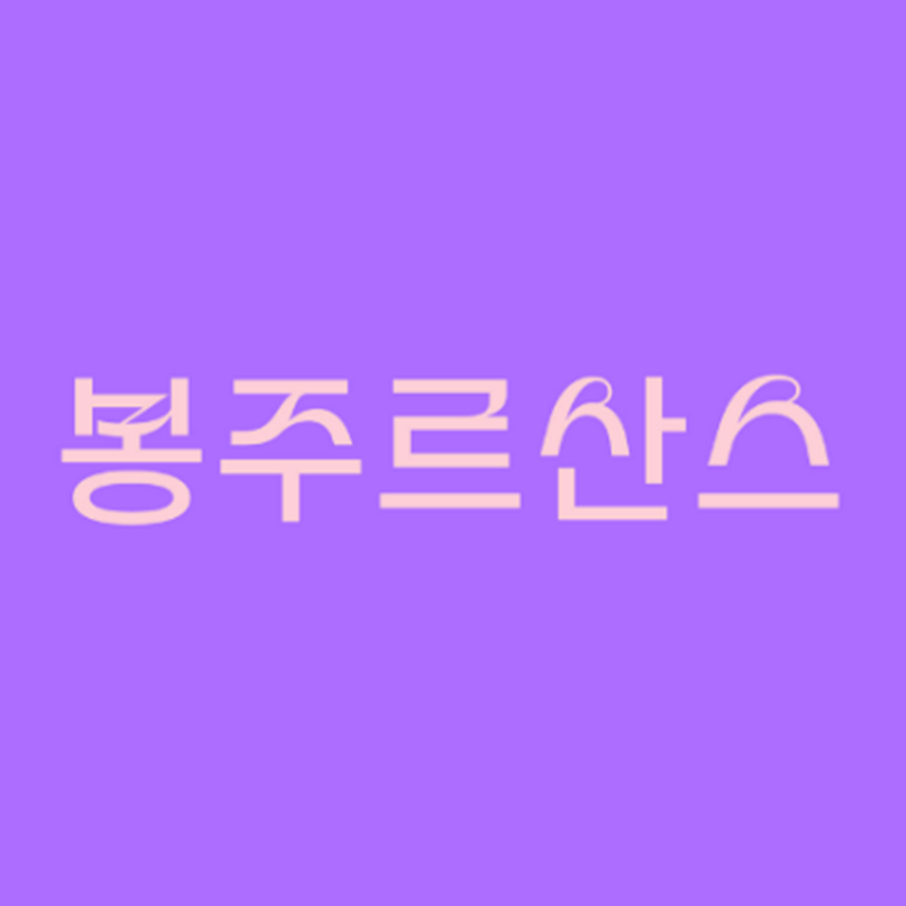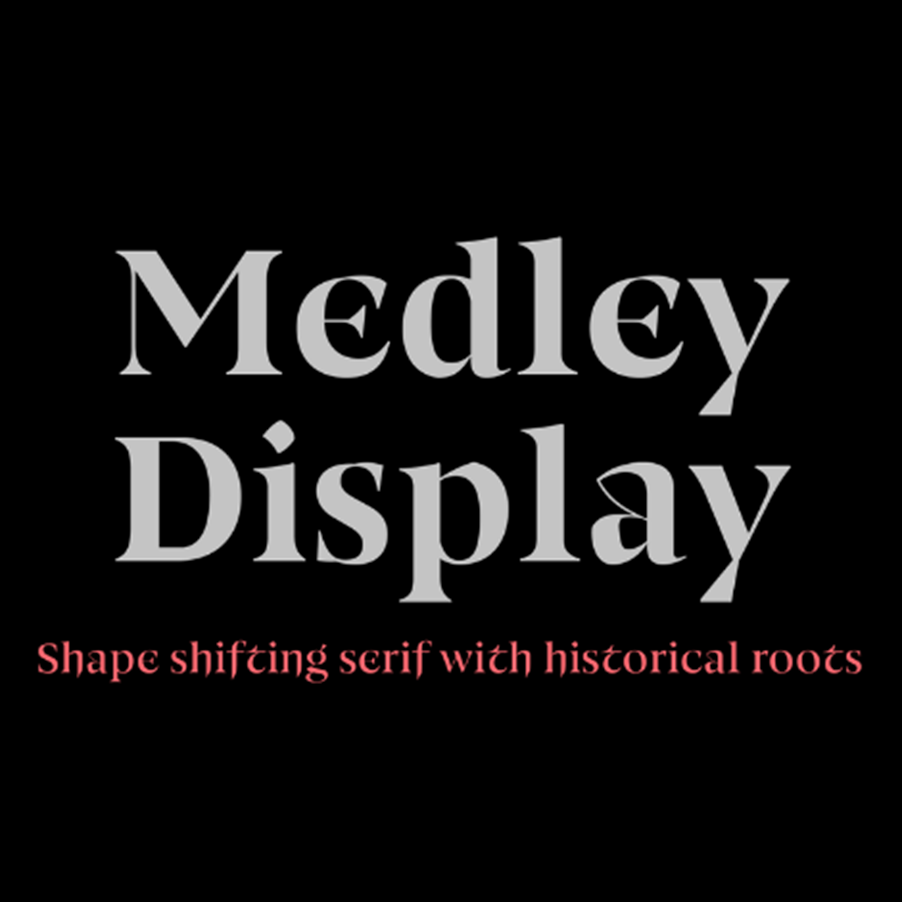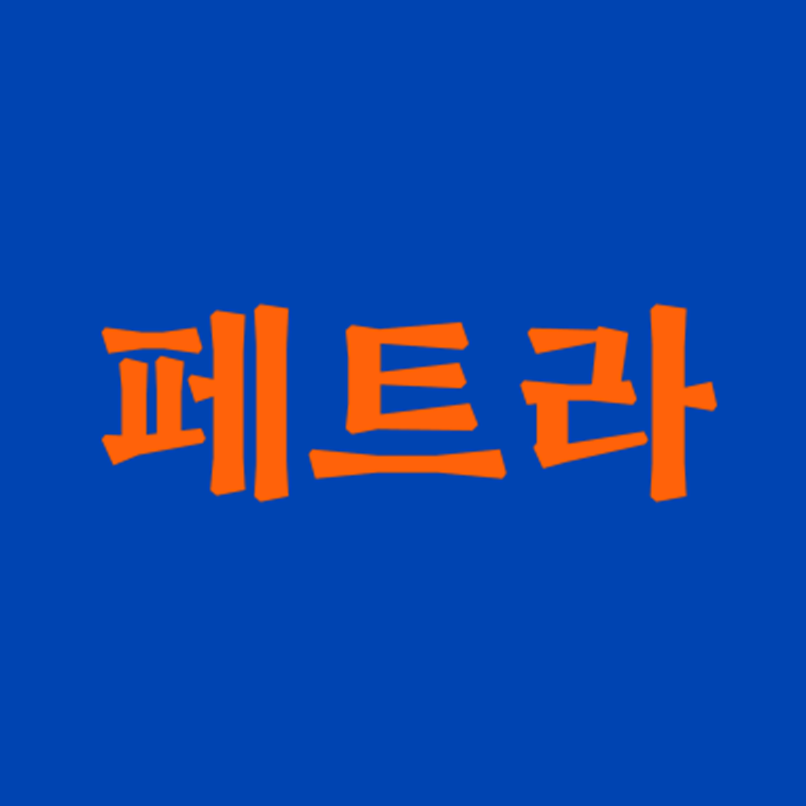
이국적 느낌 물씬~! 폰트로 떠나는 세계여행
2023년 12월 산돌구름 추천 폰트 4선
디자이너나, 창작자분들이라면 폰트 하나로 작품 혹은 창작물의 분위기가 바뀌는 경험 한 번쯤은 해보셨을 텐데요. 신비로운 무드로 이국적 느낌이 물씬 풍기는 산돌구름의 폰트 4종을 통해 세계여행 분위기를 내보는 건 어떨까요? 산돌구름의 이국적인 폰트 4종을 소개합니다.
1. 산돌 / SD페트라
「SD 페트라」는 SF소설 <듄>의 배경처럼 날카로운 모래 바람이 부는 환경을 상상하며 기획한 폰트입니다. 사람이 쓴 듯한 자연스러운 형태이지만 날카롭게 깎아내린 획이 특징이에요. 용도에 따라 2가지 스타일로 나뉘어져 있어, 긴 글줄과 작은 크기로 사용하는 경우엔 텍스트(Text), 큰 크기의 헤드라인에 사용하는 경우엔 디스플레이(Display) 스타일을 사용해보세요. 한글과 라틴, 라틴 확장, 현대 그릭 문자까지 지원하는 「SD 페트라」를 만나보세요!
2. 타입세트컴퍼니 / TSC봉주르산스
타입세트컴퍼니를 대표하는 ‘TSC봉주르산스’는 엣지있는 곡선과 이음획이 매력적인 폰트입니다. 전체적으로 모던한 인상의 디자인과 잘 어울리며, 그 중에서도 눈에 띄는 개성을 표현하고자 할 때 효과적으로 사용할 수 있어요! 기본 봉주르산스에서 디테일이 정제된 본문용 텍스트(Text) 스타일과, 더 두꺼운 굵기의 볼드(Bold) 스타일까지 함께 제공하니 다양한 크기의 제작물에서 봉주르산스를 활용해보세요.
3. 코시호타입 / Calavera
멕시코 전통 스타일이 독보적인 코시호타입의 ‘Calavera’입니다. 멕시코의 전통적인 ‘파펠 피카도’(스페인어: papel picado, 영어: chopped paper)를 모티프로 제작된 폰트로, “종이가 잘린 디자인”의 7가지 스타일과 장식 기호만으로 이루어진 1가지 스타일로 구성되어 있어요. 일반적인 한글 폰트가 아닌 어디에서도 본 적 없는 이국적인 스타일을 찾는다면, Calavera를 사용해보세요! 특별히 디자인하지 않아도 폰트만으로 디자인이 완성되는 경험을 느껴보세요.
4. 로올타입 / 메들리 디스플레이
메들리는 우아하고 장식적인 획이 특징인 라틴 폰트입니다. 특히 ‘e’, ‘t’의 모양은 다른 폰트에서 볼 수 없는 특이한 형태이지만 전체적인 스타일은 조금 더 익숙한 형태로 제작되어 균형감을 가지고 있습니다. 짧은 텍스트에서도 시각적으로 강조되는 효과를 줄 수 있고, 제목이 아닌 본문용으로 쓸 때는 비교적 획 대비가 적은 텍스트(Text) 스타일을 사용하면 조금 더 높은 가독성을 제공할 수 있어요. 예술적인 분야의 제작물에 메들리 디스플레이&텍스트를 사용하여 감각적인 인상을 높여보세요!